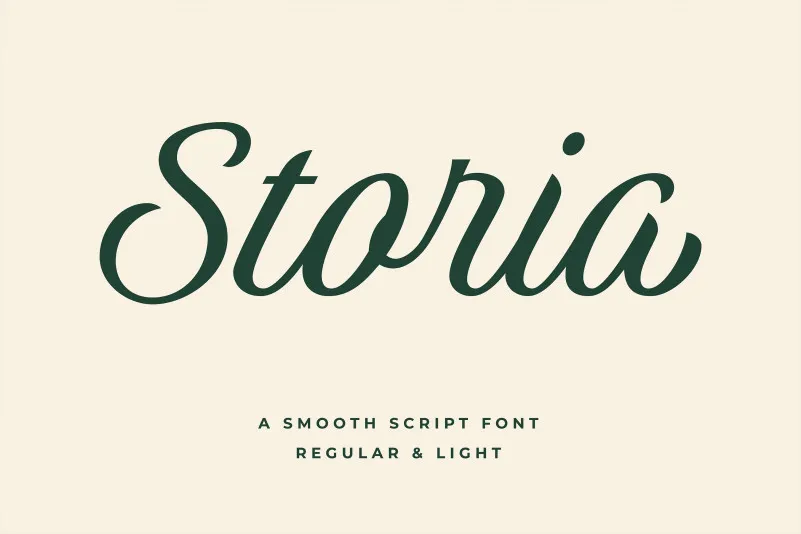
A fonte ‘Storia Font’ é uma elegante escolha para quem busca um estilo retrô e sofisticado. Desenvolvida pela Letteralle, esta tipografia é inspirada no estilo de script vintage e oferece duas opções de traço: regular e leve. Seu design único e estiloso fazem dele um recurso perfeito para qualquer aplicação visual – desde a criação de marcas e materiais promocionais até as mídias sociais e embalagens, ela se destaca como uma fonte que pode ser usada em uma variedade incrível de projetos. Seja para dar vida à sua marca ou tornar seus materiais mais atraentes, ‘Storia Font’ é um excelente investimento para seu portfólio gráfico. Com 99designs como seu designer, você pode estar certo de que está recebendo o melhor na qualidade e personalização.